Стереотипная печатная форма: как из газетной полосы отливали изогнутую пластину
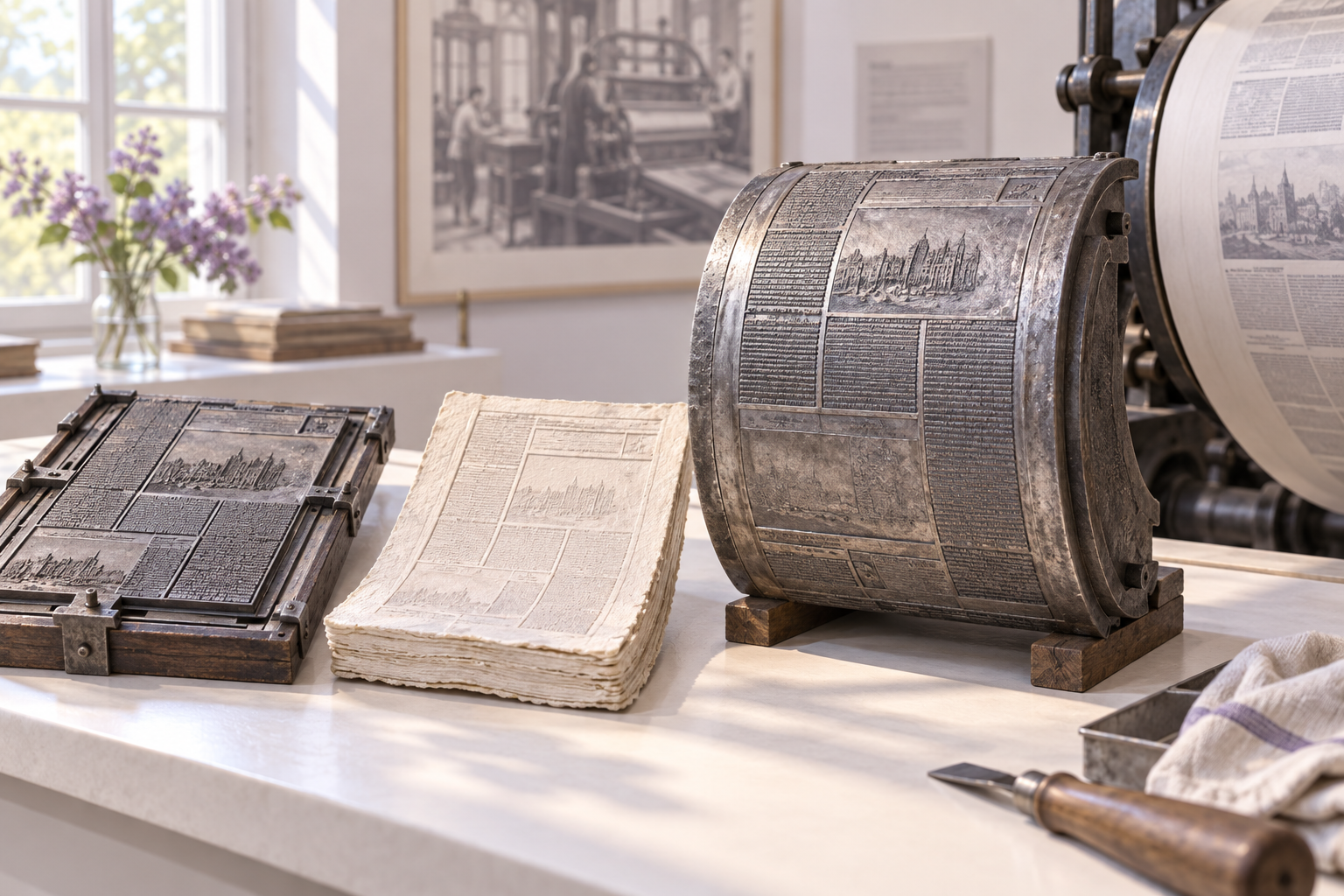
Стереотипная форма — это металлическая копия уже свёрстанной полосы, отлитая по матрице. Она позволяла оставить исходный набор свободным для другой работы и получить изогнутые пластины для ротационной газетной машины. Разберём, как готовили мат, зачем ему придавали форму полуцилиндра и как сегодня отличить матрицу от готовой пластины, если вы изучаете старую печатную продукцию или музейный предмет.
Зачем копировать готовую полосу
При высокой печати текст и иллюстрации сначала собирали в плоскую форму: литеры, пробельный материал и клише закрепляли в раме. С этой формы можно было печатать напрямую, пока она оставалась собранной. Но крупной газете требовались длинные тиражи, несколько печатных машин и повторное использование шрифтового материала. Если оставить набор в прессе, он занимал литеры и мог изнашиваться; если разобрать его сразу, повторный запуск требовал бы новой сборки.
Стереотипирование отделяло форму от этой дилеммы. С плоского набора снимали рельефную матрицу, а по ней отливали копию страницы из типографского металла. В пресс отправляли уже копию, а литеры исходной формы можно было разобрать и вернуть в работу. Если одна и та же полоса требовалась на нескольких машинах, с одной матрицы отливали несколько пластин. Музей печати в Мельбурне описывает этот процесс как способ получать повторяемые блоки с набранного текста или гравюры и при необходимости передавать один и тот же материал разным печатникам.
Это важно отличать от изготовления отдельной литеры. В словолитне пуансон и матрица служили для отливки множества одинаковых знаков. При стереотипировании матрица снималась не с буквы, а со всей готовой композиции страницы — вместе с пробелами, строками и клише.
Мат, матрица и стереотип — три разных предмета
В описаниях старой типографии легко перепутать названия, потому что «матрицей» называют несколько негативных форм в разных производственных процессах. Для газетного стереотипирования полезно держать простую последовательность:
- *Наборная форма* — исходная плоская композиция, закреплённая в раме. Лицевые поверхности литер выступают на печатную высоту.
- *Мат, или флонг* — гибкий оттиск с этой формы, который принимает рельеф букв и изображений. Он работает как отрицательная форма для последующей отливки.
- *Стереотипная пластина* — металлическая копия страницы, полученная по мату. Это уже печатная поверхность с выступающими элементами.
- *Цилиндрическая пластина* — та же копия, отлитая с кривизной, чтобы закрепить её на барабане ротационной машины.
На практике слово «матрица» могло употребляться и для мата, и для формы, от которой он получен. Поэтому при чтении каталога, инвентарной карточки или подписи сначала выясняйте, что именно описывается: гибкий негатив, плоская исходная форма или металлическая копия. Фраза «сняли мат с полосы» означает один этап; «отлили стереотип» — следующий.
Как получали мат с наборной формы
Сначала полосу собирали и проверяли как обычный набор. В форму могли входить не только наборные строки, но и клише иллюстраций. Перед тиснением формы на мат особенно важно было зафиксировать композицию: после снятия отпечатка исправление опечатки уже затрагивало не только отдельную литеру в копии, а подготовку нового мата или корректировку всей цепочки.
Ранние бумажные маты собирали из тонкой бумаги: её притаптывали или простукивали в пробельные углубления специальной щёткой, затем добавляли более плотные слои. Позднее стали использовать готовые многослойные листы — флонги. Их увлажняли до нужной гибкости, накрывали мягкой прокладкой и прессовали на форме. Музей печати Мельбурна описывает как ручное формование тонкой бумаги, так и более поздний прессованный флонг.
Главная задача была получить мат, в котором отпечатались бы мелкие детали, но сама наборная форма не деформировалась. Для защиты литер при сильном прессовании вокруг набора применяли металлические ограничительные полосы — бейреры. Их след мог появиться на отлитой пластине как рамка. Мат снимали и просушивали; по одной наборной форме можно было подготовить несколько матов.
От гибкого мата к металлической копии
Подготовленный сухой мат помещали в литейную форму. В неё заливали типографский сплав, который заполнял углубления, оставленные выступающими литерами и клише. После охлаждения мат отделяли: на металлической стороне получалась обращённая к печати поверхность страницы. Отливку обрезали, выравнивали по высоте и готовили к креплению в печатной форме или на цилиндре.
Это не фотокопия страницы. Изображение переносилось через физический контакт: исходная рельефная поверхность формировала негативный рельеф в мате, а расплав повторял этот негатив уже в металле. Поэтому стереотип мог воспроизводить мелкие штрихи и точечный рисунок полутонового клише, если они присутствовали в исходной форме и мат их передал.
Музейный предмет сам по себе хорошо показывает, что «стереотип» — не абстрактный термин. В коллекции Science Museum Group хранится изогнутая свинцовая пластина первой полосы Daily Telegraph от 31 декабря 1985 года — последнего стереотипного выпуска газеты в манчестерской типографии Thompson House. После переезда производство перешло на рулонную офсетную печать. Это конкретный конец локальной производственной эпохи, а не дата исчезновения стереотипирования повсюду.
Стереотипирование превращало плоскую наборную полосу в копируемую металлическую форму; её изогнутый вариант сделал композицию пригодной для ротационной газетной машины. Чтобы исследовать старую печать, проследите цепочку «наборная форма → мат → отливка», уточните тип пресса и укажите, какие признаки подтверждены источником. Так техническая история страницы становится проверяемой, а не основанной на догадке по одному скану.